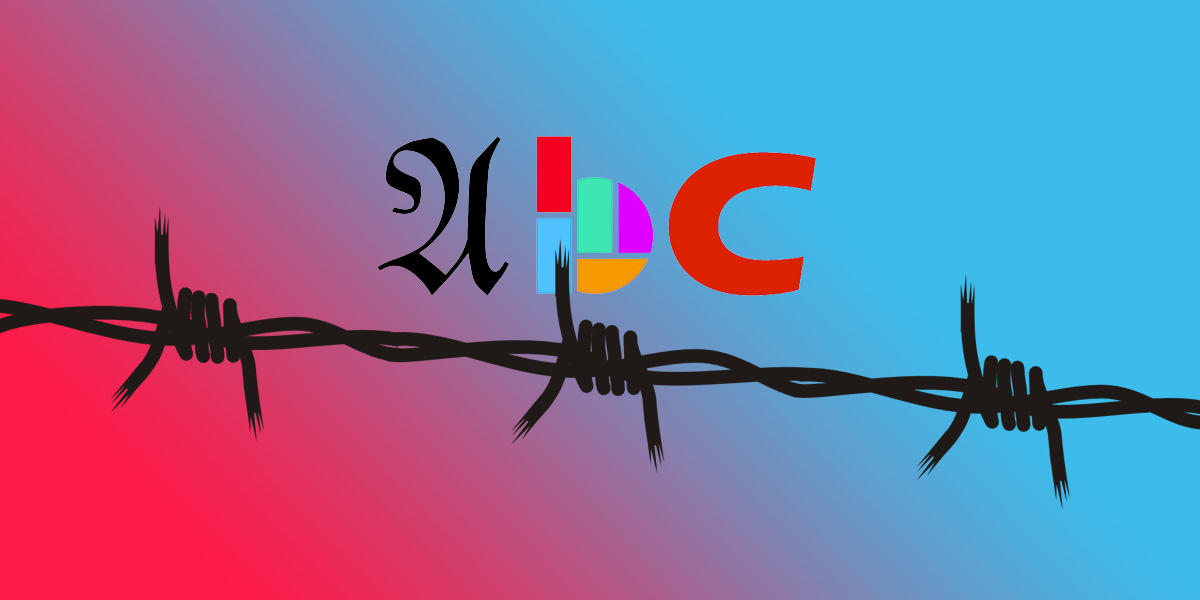
Bento.de, der Spiegel-Online-Ableger für hippe Junge, die News und Kommentar gern in sehr handlichen Häppchen serviert bekommen (und von Fremden gern geduzt werden), hat sich doch tatsächlich getraut, das Symbol-Bild eines Glossars zum Thema Flüchtlinge mit einem echten, traditionellen Fraktur-A zu illustrieren. Das stimmt uns doch hoffnungsfroh, oder?
Nur was bedeutet das A? Warum ist es schwarz?
Das muss so. Ist schließlich ein Blackletter-A. :party:
Ansonsten gibt mit die Gestaltung einige Rätsel auf. Aber darum ging’s mir nicht.